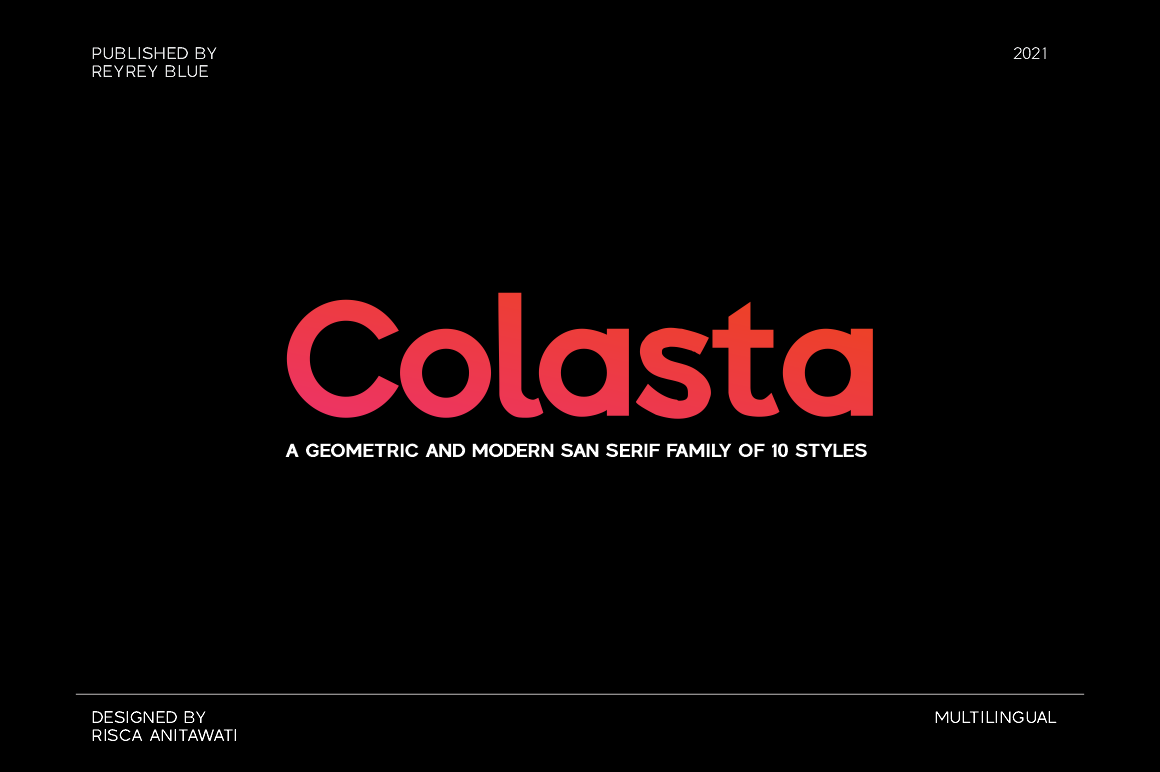
A fonte Colasta é uma nova família de tipo geométrico sans-serif projetada para adicionar uma aparência moderna a qualquer design. Esta fonte se destaca por sua versatilidade, oferecendo 10 estilos diferentes que incluem suporte a maiúsculas pequenas e caracteres de gíria para várias línguas. A Colasta é perfeita tanto para textos quanto para aplicações visuais como marca própria, anúncios, outdoors, embalagens, headlines de revistas ou sites, design de logotipos, banners e até mesmo design para redes sociais. Com a Colasta, você terá uma fonte versátil que se encaixa em um amplo espectro de aplicações gráficas.